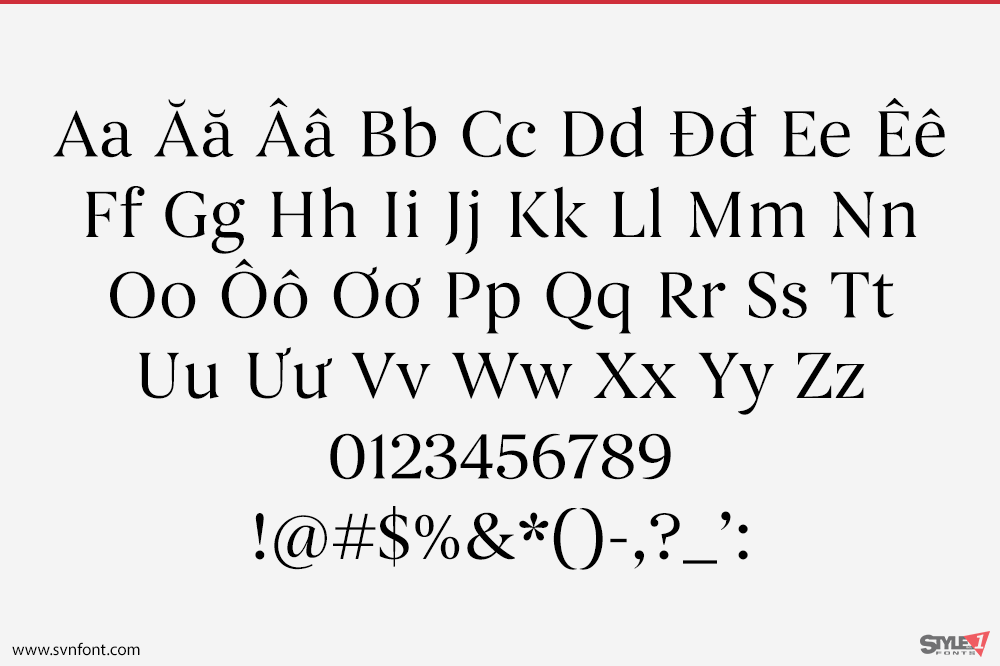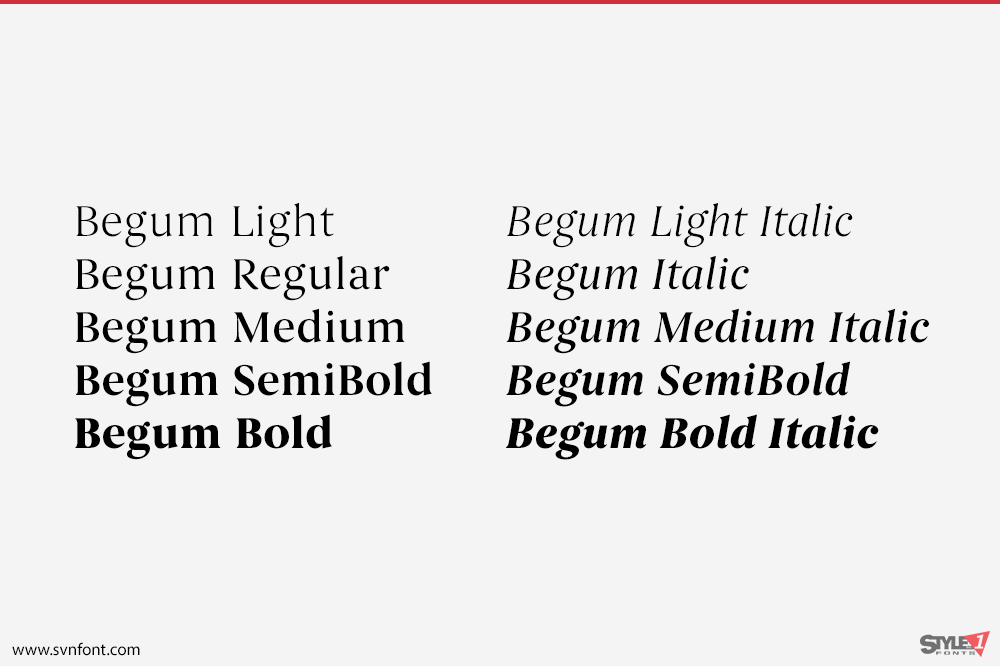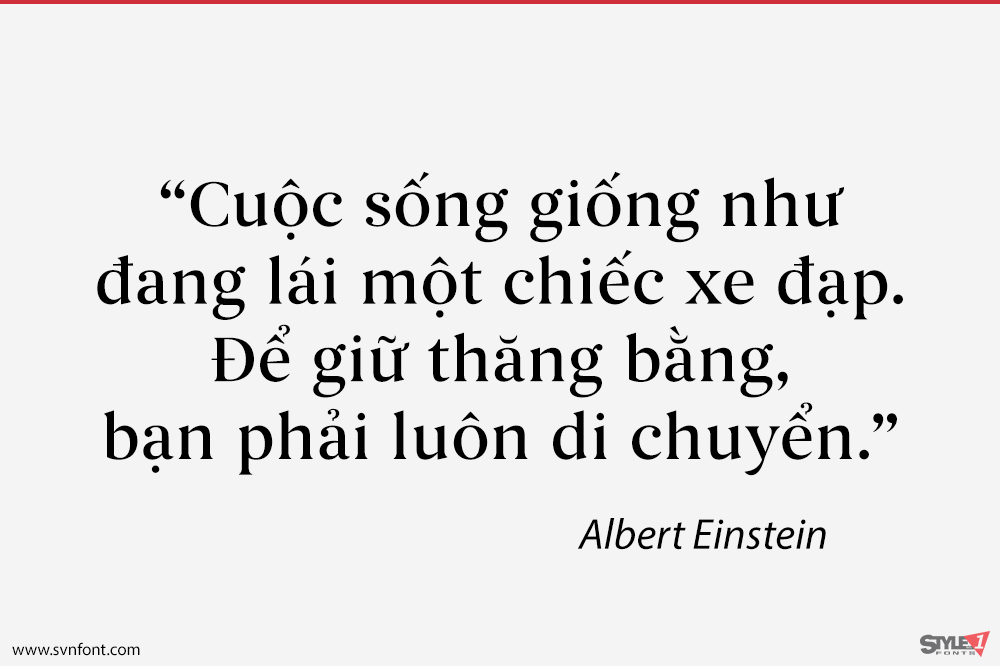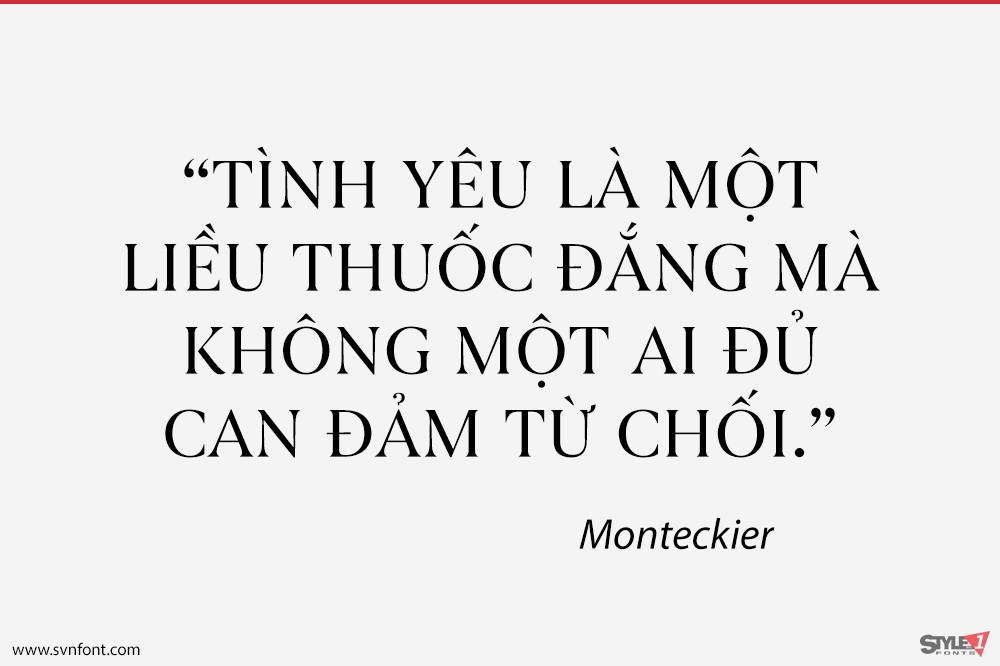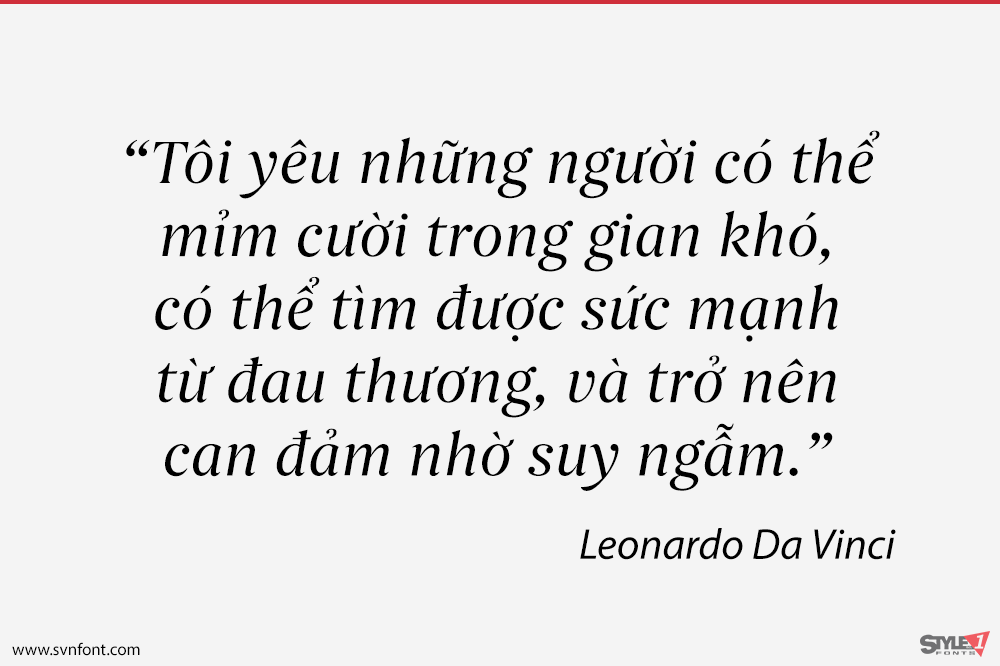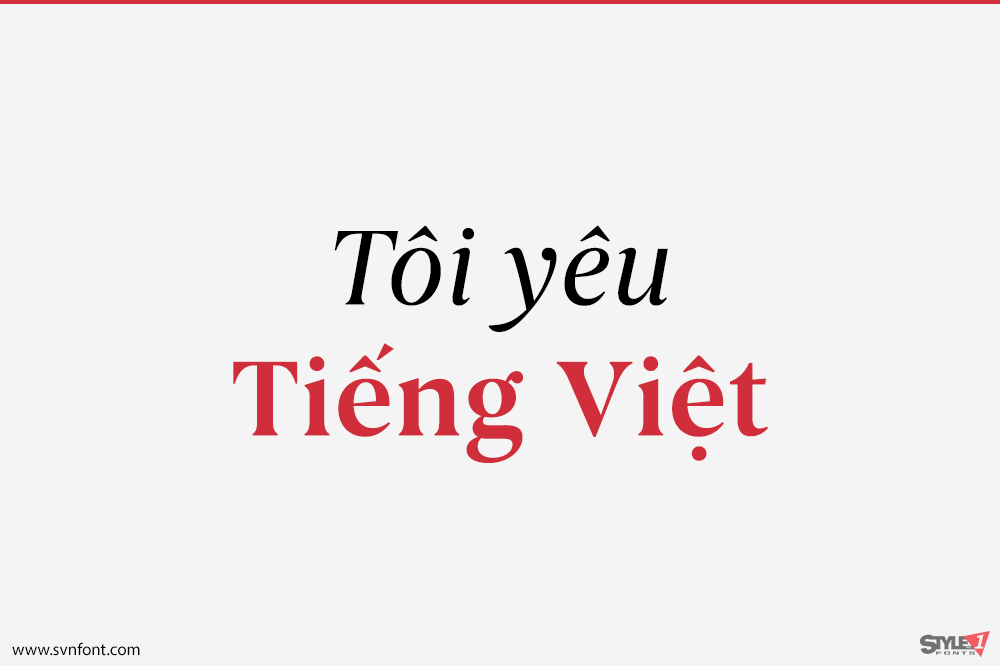
Begum là một kiểu chữ serif Latinh có độ tương phản, được dùng để hiển thị. Với vẻ ngoài cực kỳ hiện đại, các ký tự của nó mang dấu ấn của các kiểu chữ kinh điển Anh-Hà Lan như Caslon, Fleischmann hay Times.
Bộ phông chữ này rất nổi bật khi dùng cho các đoạn văn bản ngắn, phần giới thiệu bài viết nhiều dòng, và thậm chí cả trên bao bì. Begum là một phần của một bộ phông chữ lớn hơn, cũng hỗ trợ các bộ chữ Devanagari và Tamil.